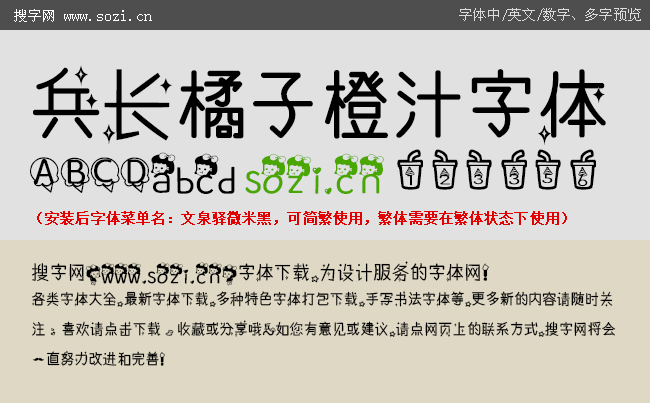
兵長(zhǎng)橘子橙汁字體
搜字網(wǎng)給大家提供一款名為兵長(zhǎng)橘子橙汁字體的手機(jī)中文字體下載。這款手機(jī)字體是以黑體字體為原形,筆畫(huà)進(jìn)行了重新設(shè)計(jì),帶家兒童卡通風(fēng)格,字體間還插入了一些卡通圖案,使字體更具趣味性,喜歡的朋友安裝一下吧。